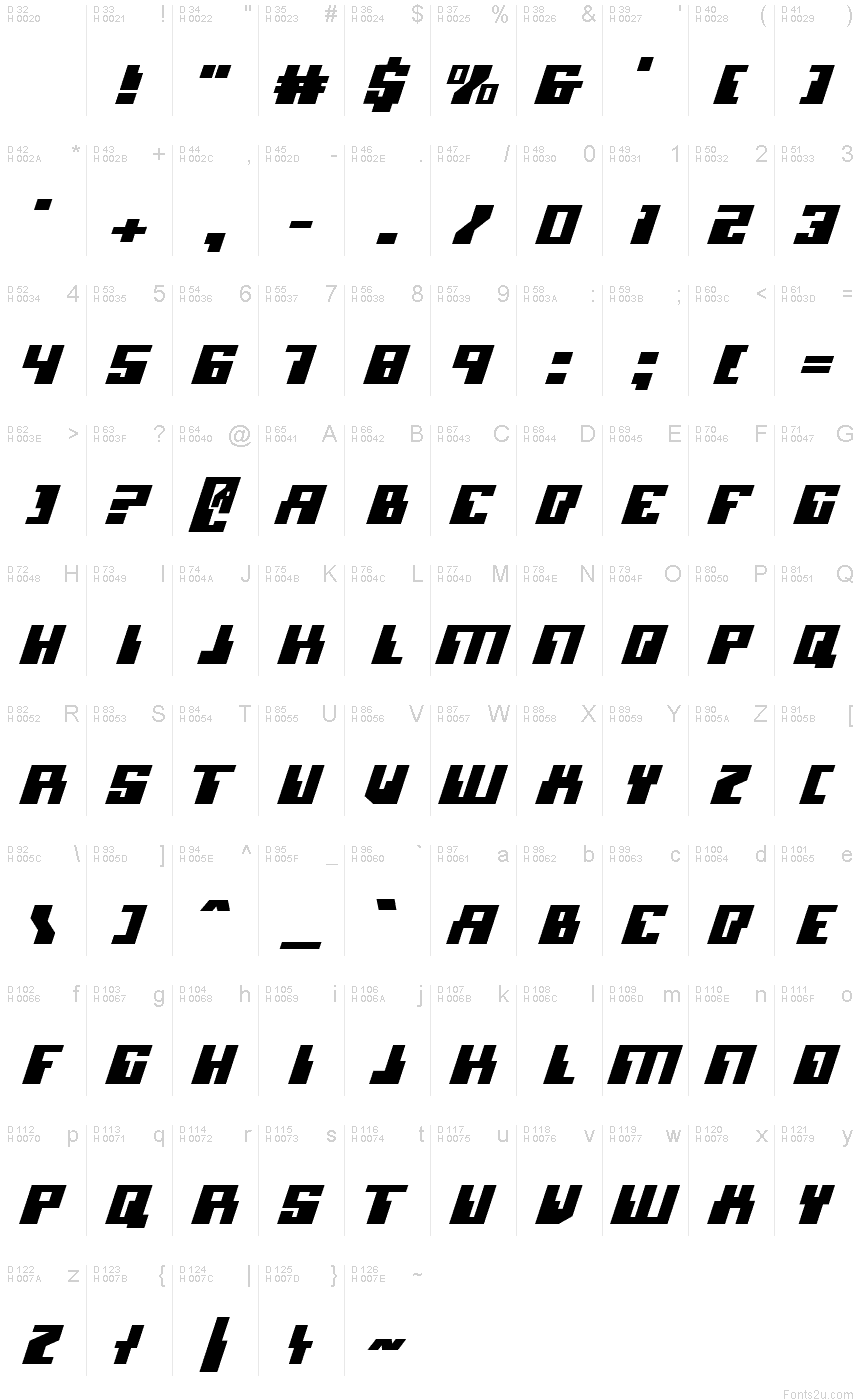
Micronian Italic von Iconian Fonts ist eine kostenlose, kantige Techno-Display-Schrift mit einer starken Neigung nach vorn. Breite Striche, scharfe diagonale Schnitte und quadratische Aussparungen verleihen den Buchstaben das Aussehen segmentierter Maschinenpaneele.
Themen wie Technologie und Science-Fiction prädestinieren sie für Spieloberflächen, Filmgrafiken und E-Sport-Branding. Ihre kompakten, aggressiven Formen eignen sich als Benutzeroberflächen-Beschriftungen oder als Teil eines mechanischen Emblems. Auch Plattenhüllen und Event-Poster passen zu ihrem schnellen, industriellen Stil.
Micronian Italic